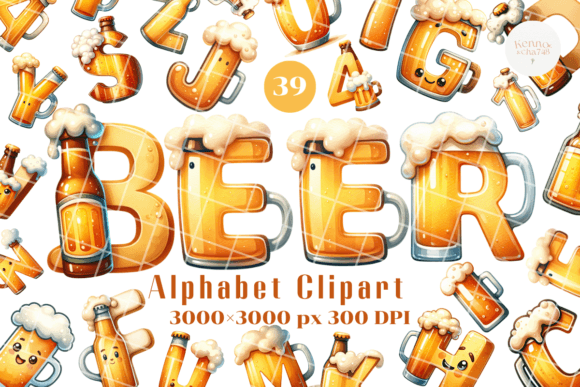
A-Z Beer Themed Alphabet Clipart - Craft
Die richtigen Designelemente zu finden, kann eine Herausforderung sein, aber A-Z Beer Themed Alphabet Clipart - Craft bietet eine außergewöhnliche Sammlung, die Ihre Arbeit sofort aufwertet.
Mit Präzision gefertigt, bietet A-Z Beer Themed Alphabet Clipart - Craft saubere Vektoren, eine reibungslose Typografie und eine kommerzielle Lizenz für ein beruhigendes Gefühl.
Egal, ob Sie POD-Produkte (Print on Demand), Hochzeitseinladungen oder Social-Media-Grafiken erstellen, A-Z Beer Themed Alphabet Clipart - Craft ist die ideale Wahl.